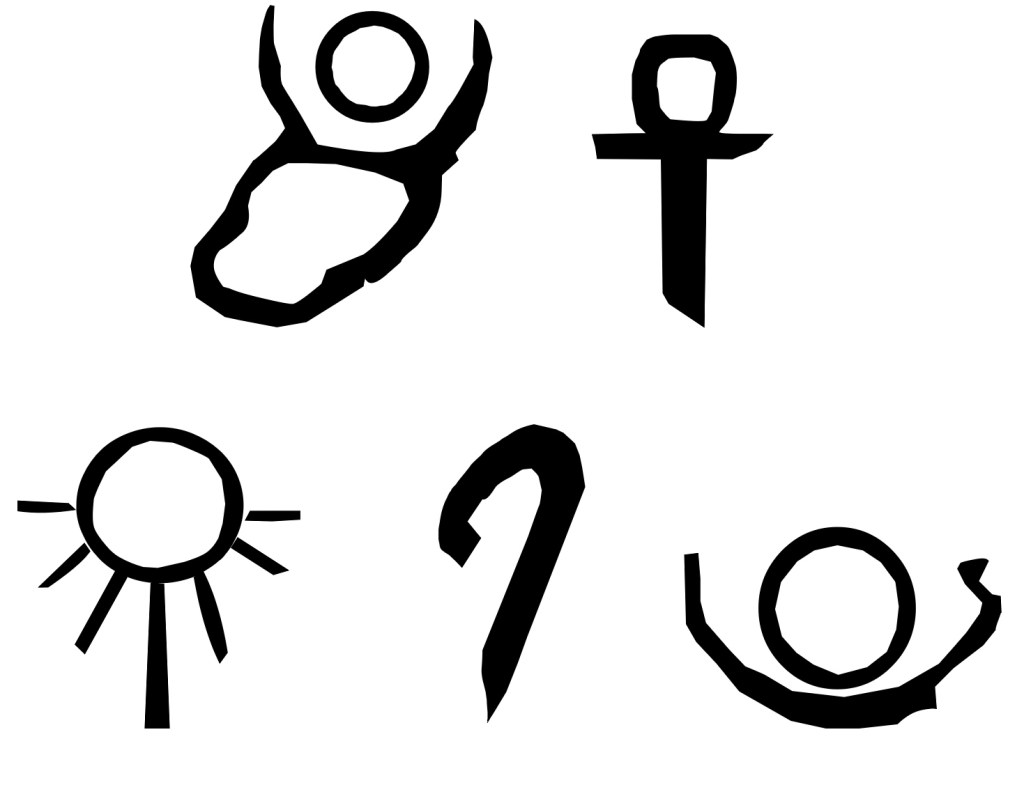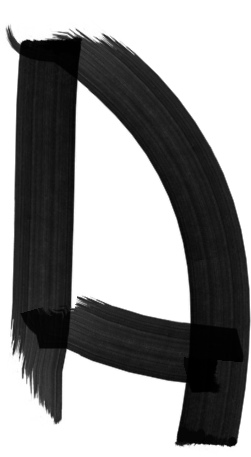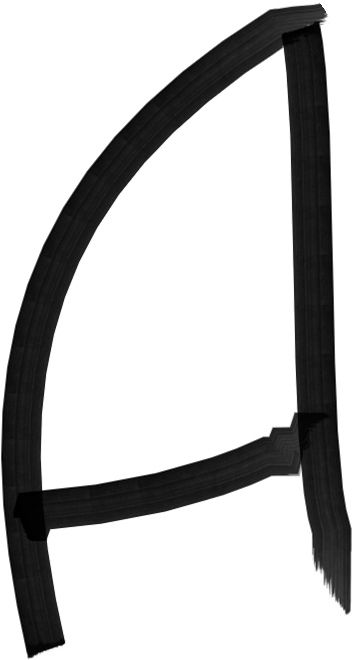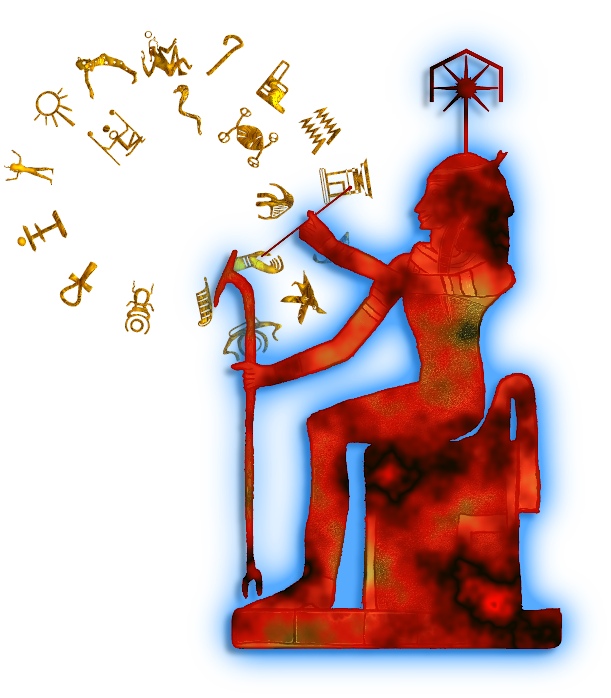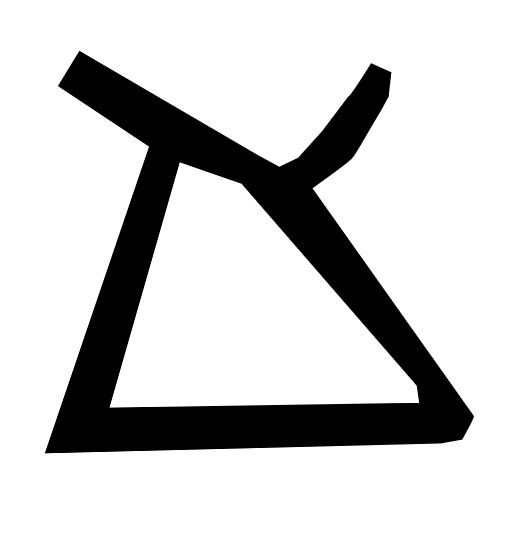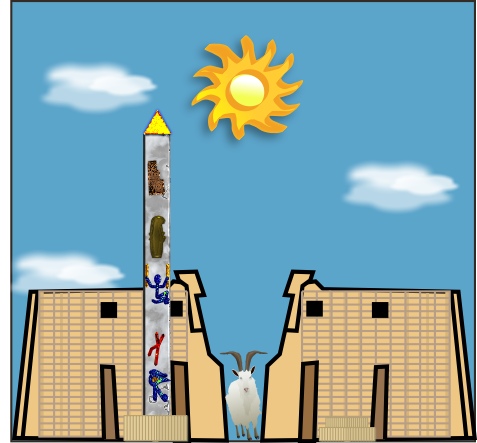
Si l’on gratte, en passant par les sables, les tombes et les temples, nous découvrons que la source des sources des écritures alphabétiques est Égyptienne et que sur les 20 signes originaux, ceux qui nous sont parvenues via le latin, 18 représentent les divinités majeures, auxquelles s’ajoutent le concept de la vie et celui du pouvoir. Cela parait étrange. Le plus déconcertant est que les preuves nous sont parvenues via un outil improbable : le manège équestre !
Si l’on avait le choix d’un mode d’écriture à la naissance, nous choisirions une solution simple à apprendre et la plus évolutive possible. Le binaire ou a défaut, l’hexadécimal conviendraient bien. Malheureusement, nous avons commencé à parler avant d’écrire et…
Prenons 6 entités fondamentales, dont des concepts philosophiques, ajoutons cinq variations de la plus grande divinité créatrice, ses quatre enfants et petits enfants, des forces élémentaires et enfin cinq déesses et dieux qui formeront l’essentiel des histoires épiques de la…
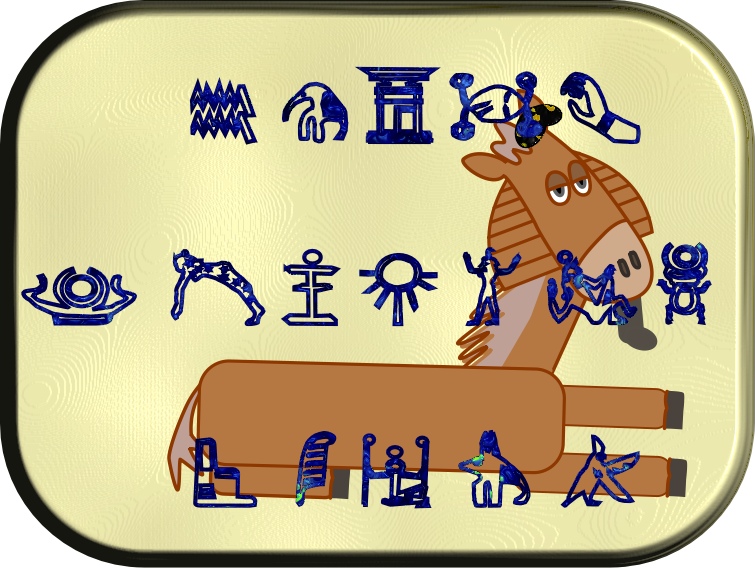
Vous ne vous êtes jamais demandé pourquoi et depuis quand le manège équestre a cette forme et ces marques si particulières ? Vous ne vous êtes jamais enquis de qui a pensé cette chose improbable ? Ce n’est pas grave, nous avons…
Une invention ou une découverte, aussi surprenante soit-elle, est toujours incluse dans un flux d’idées et d’histoires qui l’ont influencé, parfois façonné et souvent aidé à poindre. Les Lettres Données n’échappent pas à cette constatation : pour comprendre ou révéler quelque…
La question qui se pose est simple : est-ce que 4 milliards d’êtres humains s’expriment, sans trop le savoir, en hiéroglyphes sacrés aimablement sélectionnés par des scribes, il y a 4 500 ans ?
La réponse est oui.
Au début, l’idée était d’éclaircir le mystère du manège équestre, sans nous douter de l‘intrication ancestrale entre écrit, mystique et équitation !